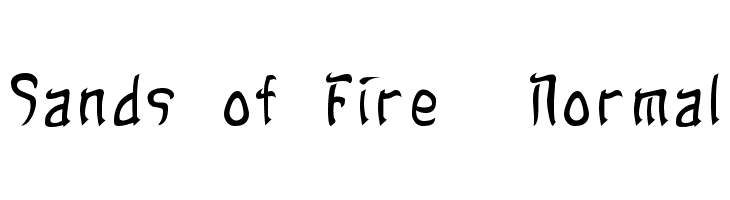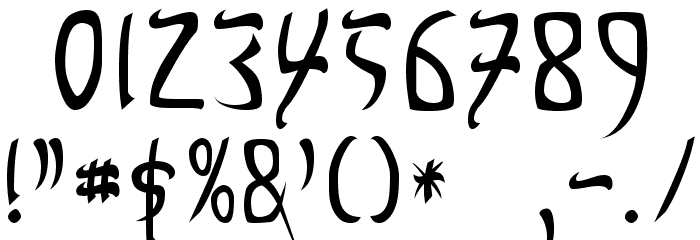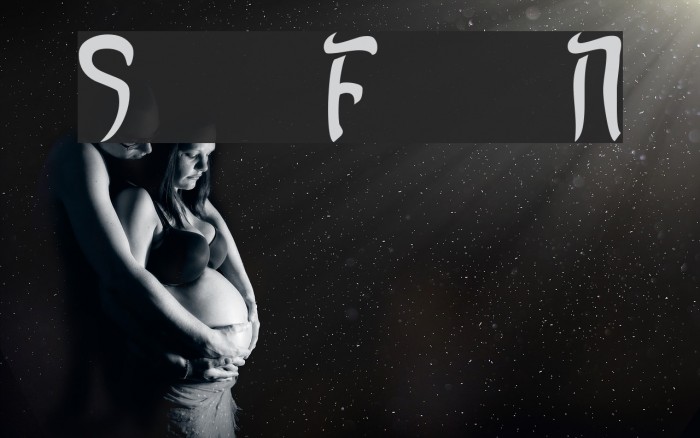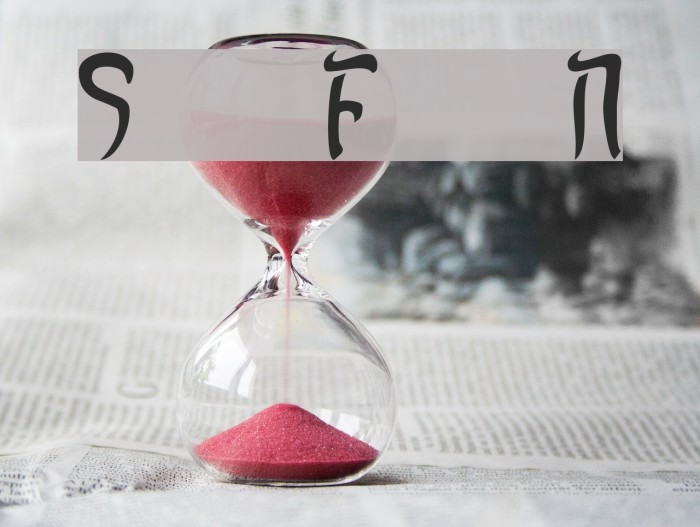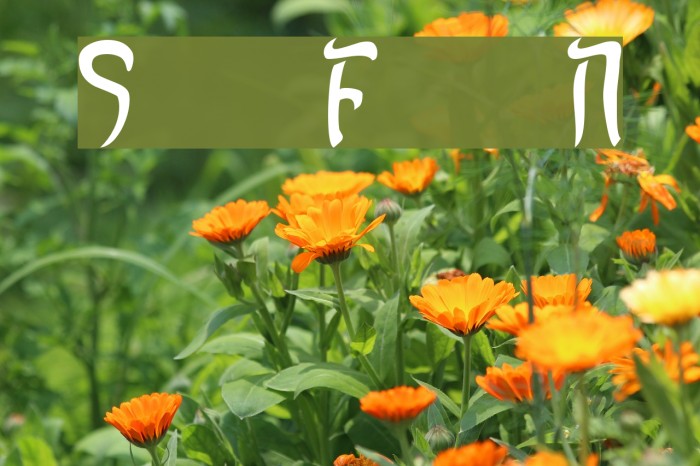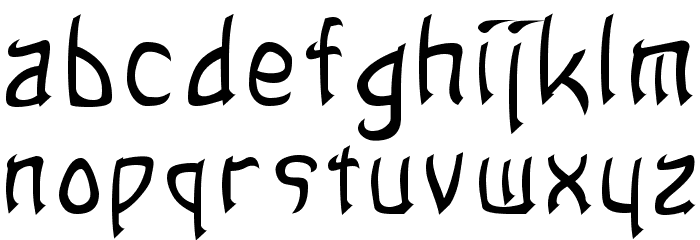
Sands of Fire Normal Font
| Vorgeschlagene Projekte | Ideal for creative projects such as posters, album covers, and branding materials where a unique and expressive typeface is desired. |